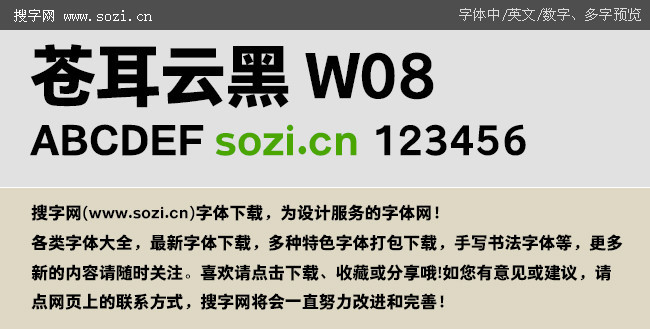
蒼耳云黑W08
搜字網給大家提供一款蒼耳云黑W08中文字體下載,倉耳云黑是中國第一款突破鉛字黑體束縛的原創(chuàng)黑體,在同類產品中筆形特征典雅現代,結體豐富容易辨識,獨具匠心的筆畫與結構的微妙結合體現出黑體獨有的字形之美,展現漢字所具有的多變、精巧的靈韻之美。適合應用于藝術設計、平面宣傳設計、網頁設計等應用。(本字體為個人非商用版,如需要商用請聯系官方購買版權)